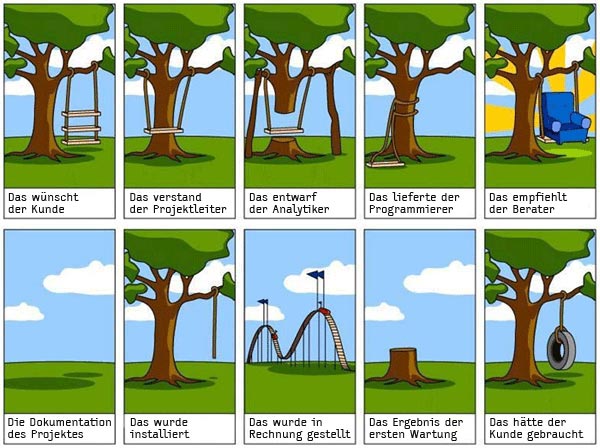
Dumm gelaufenBilder sagen manchmal mehr als Worte ... obwohl die hier verwendete Schrift wirklich sehr schön ist. Falls Sie
sich die Missdeutungen der an einem Projekt beteiligten Experten manchmal nicht
erklären können, unsere Illustration verdichtet die abweichenden
![]() Gefunden bei Autsch: die Illustration eines anonymen Künstlers fasst
die wesentlichen Missverständnisse bei der Abstimmung zwischen Auftraggeber
und den Ausführenden zusammen. Dabei ist es egal, ob es sich um ein Projekt
aus der EDV, dem Handwerk oder anderen Dienstleistungen
handelt.